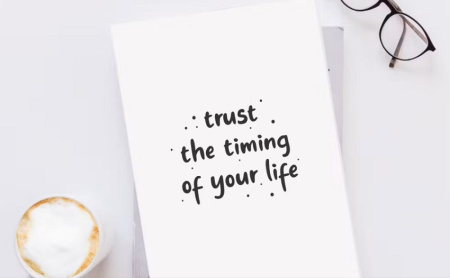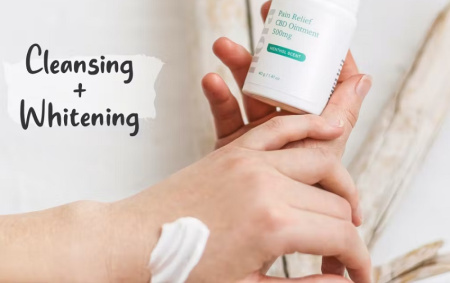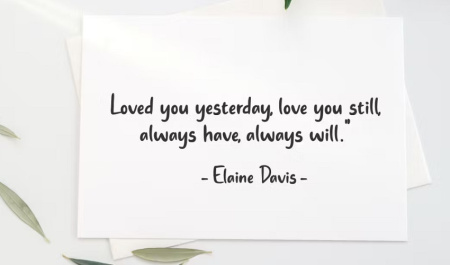
دانلود فونت رایگان انگلیسی Always Lovely
فونت رایگان انگلیسی Always Lovely
دانلود فونت رایگان انگلیسی Always Lovely یک فونت دست‌نویس به سبک مدرن است. این فونت انگلیسی برای بسته‌بندی محصول، طرح‌های محصول، برچسب، عکاسی، واترمارک، رویدادهای خاص یا هر چیزی عالی است. شما می توانید در طراحی های مختلف از این فونت انگلیسی زیبا استفاده نمایید. برای دانلود این فونت رایگان از جی اف ایکس دانلود در ادامه مطلب با ما همراه باشید.
✅ نام فونت انگلیسی: Always Lovely
✅ حروف بزرگ و کوچک
✅ اعداد و نقطه گذاری